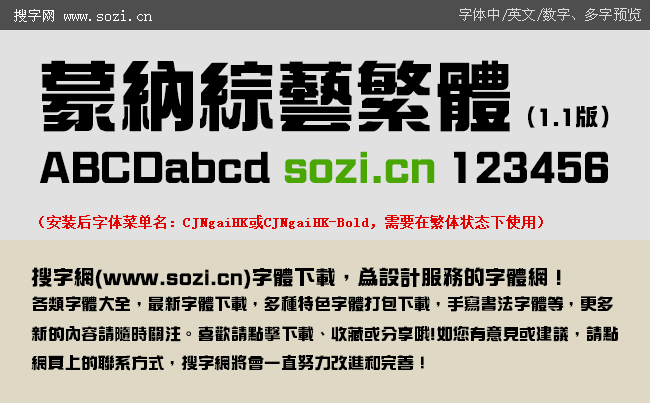
蒙納綜藝繁體
搜字網(wǎng)提供一款蒙納綜藝繁體下載。綜藝體是黑體的一種變體,也是藝術(shù)字的一種。特點是筆劃更粗,盡量將空間充滿。同時為了美觀,對拐彎處的處理較為圓潤。蒙納綜藝體筆結(jié)構(gòu)美觀,字體厚重。適用于廣告、報刊等的標題及海報展板等設(shè)計場合使用。
- 風(fēng)格類別: 綜藝體